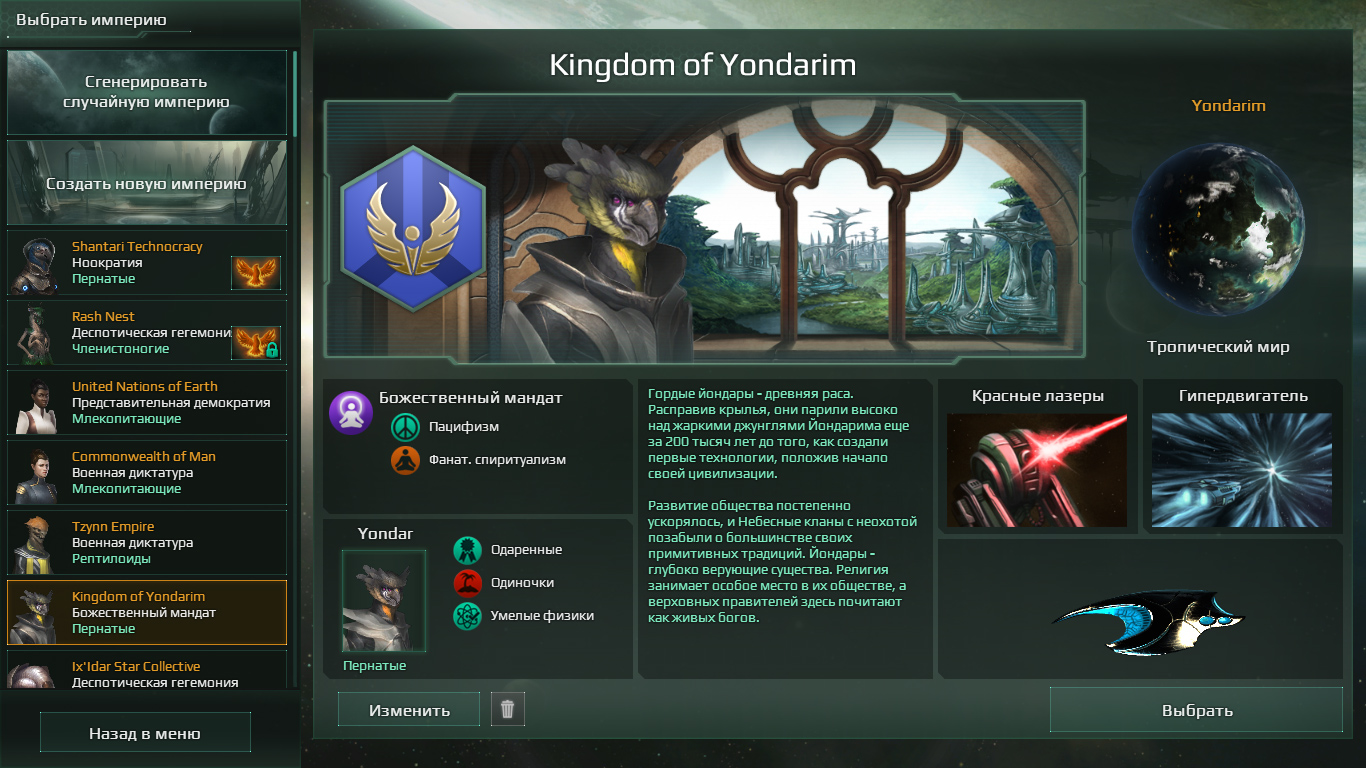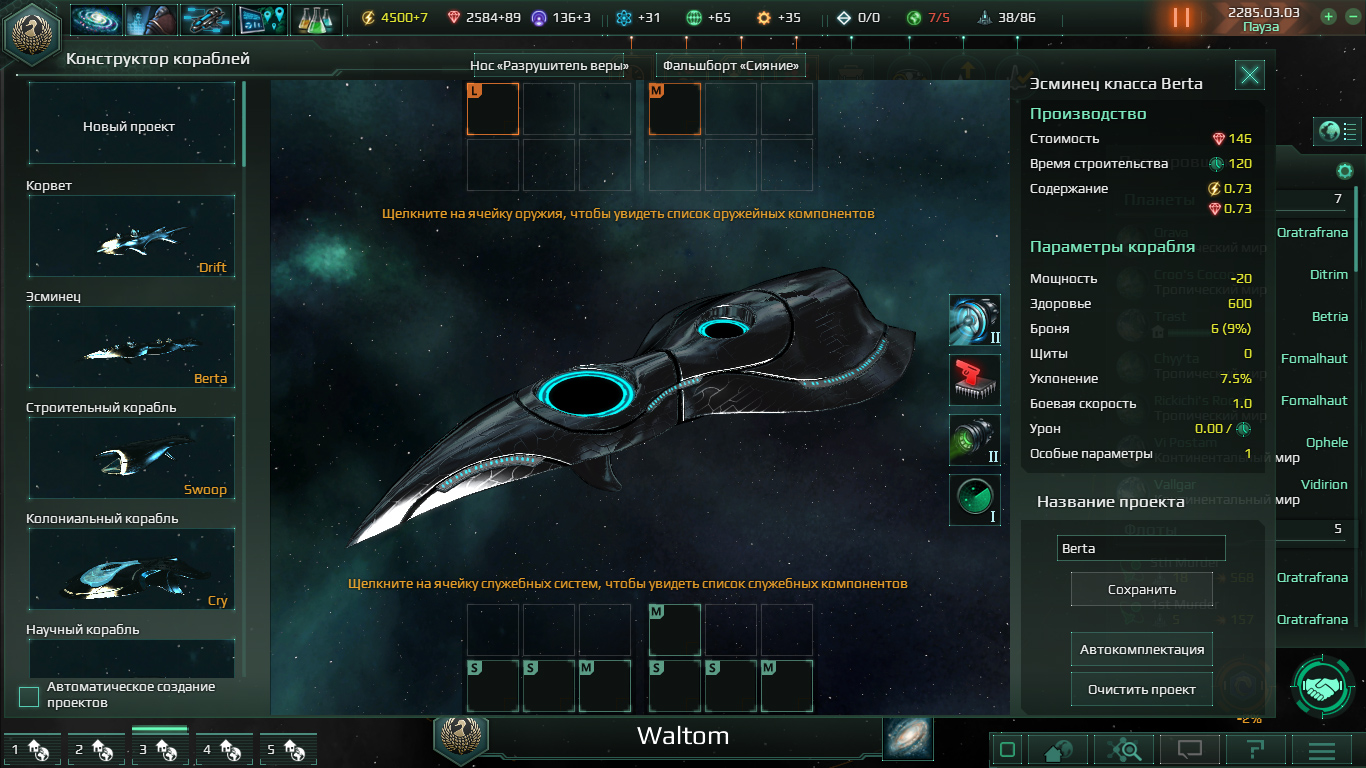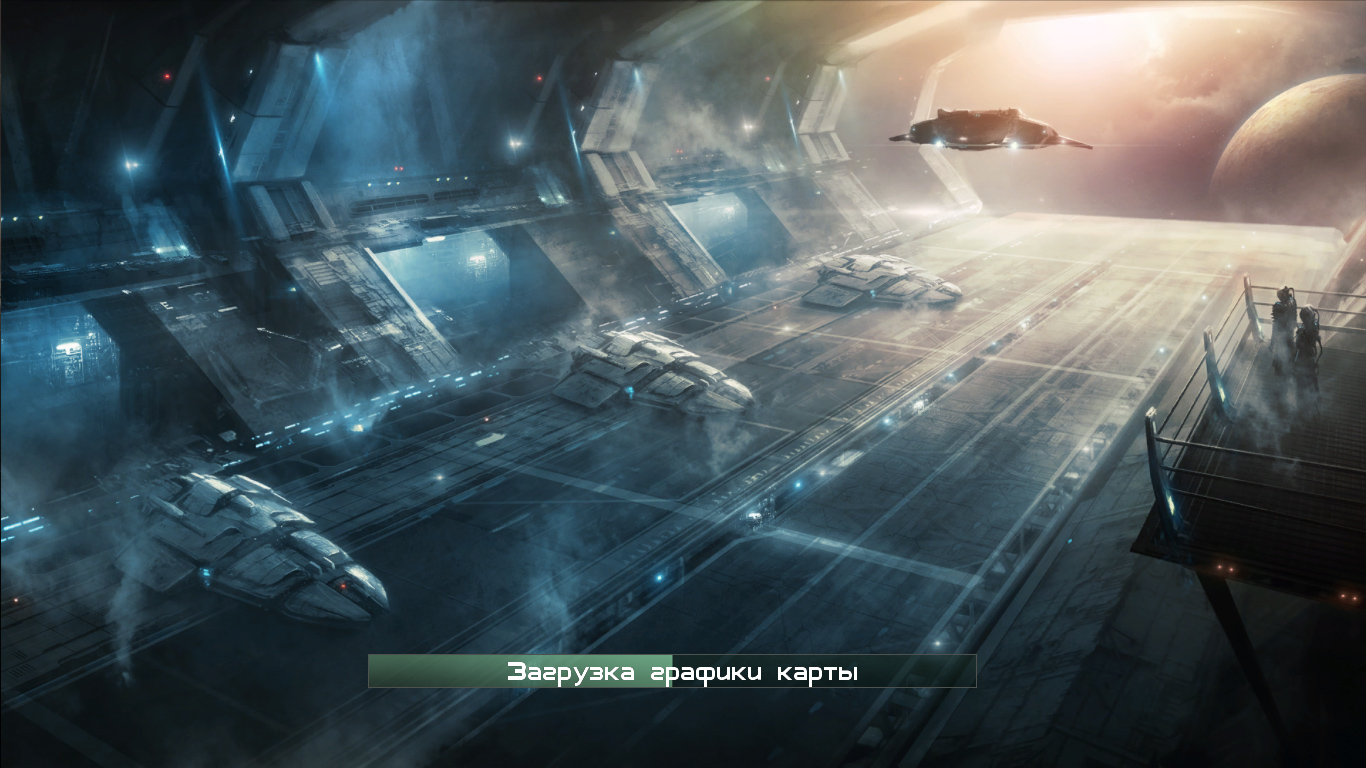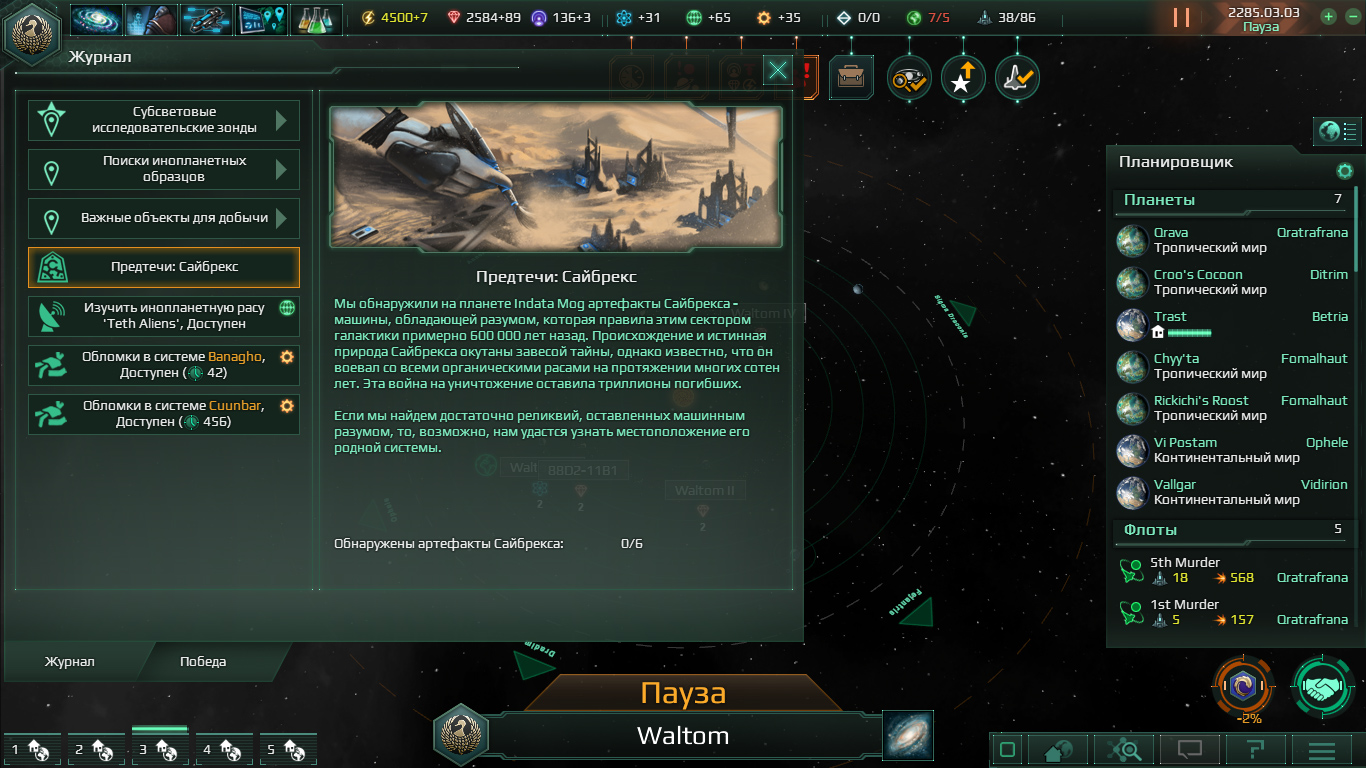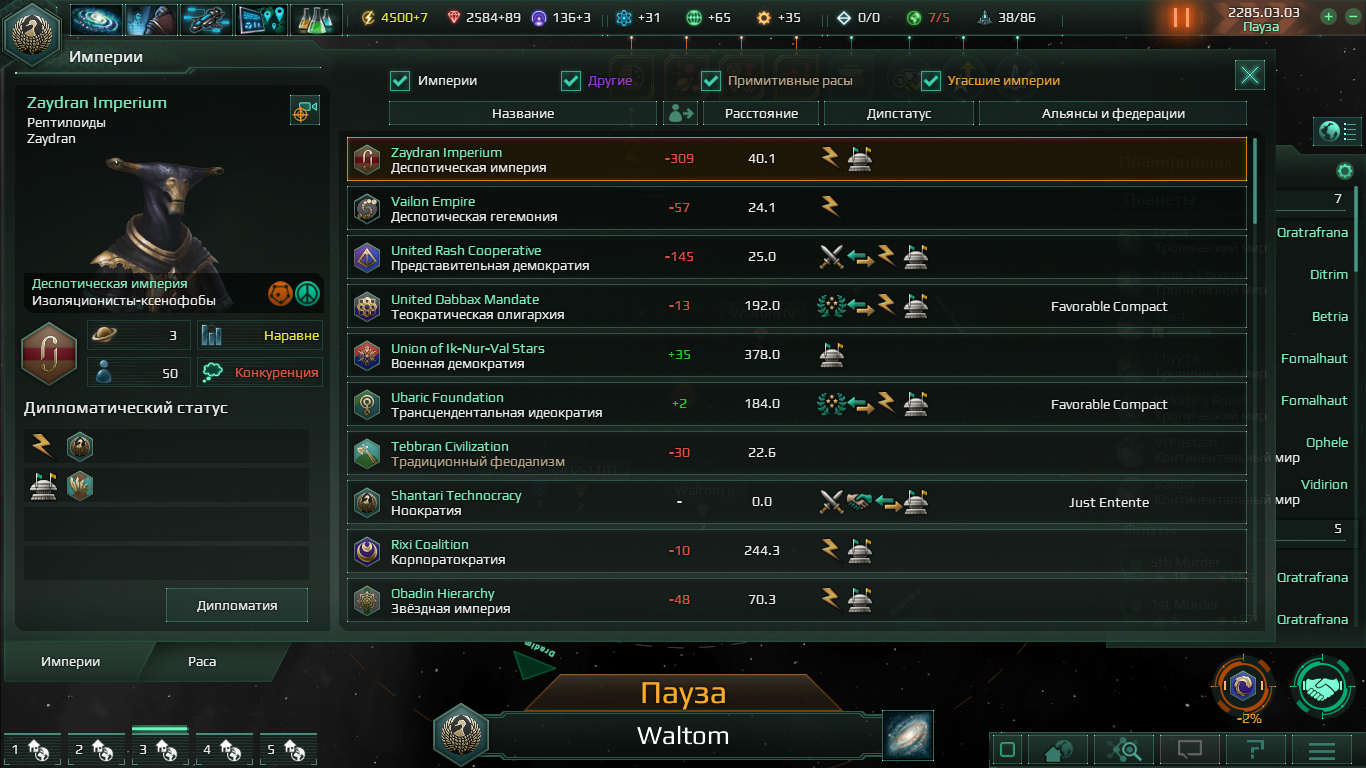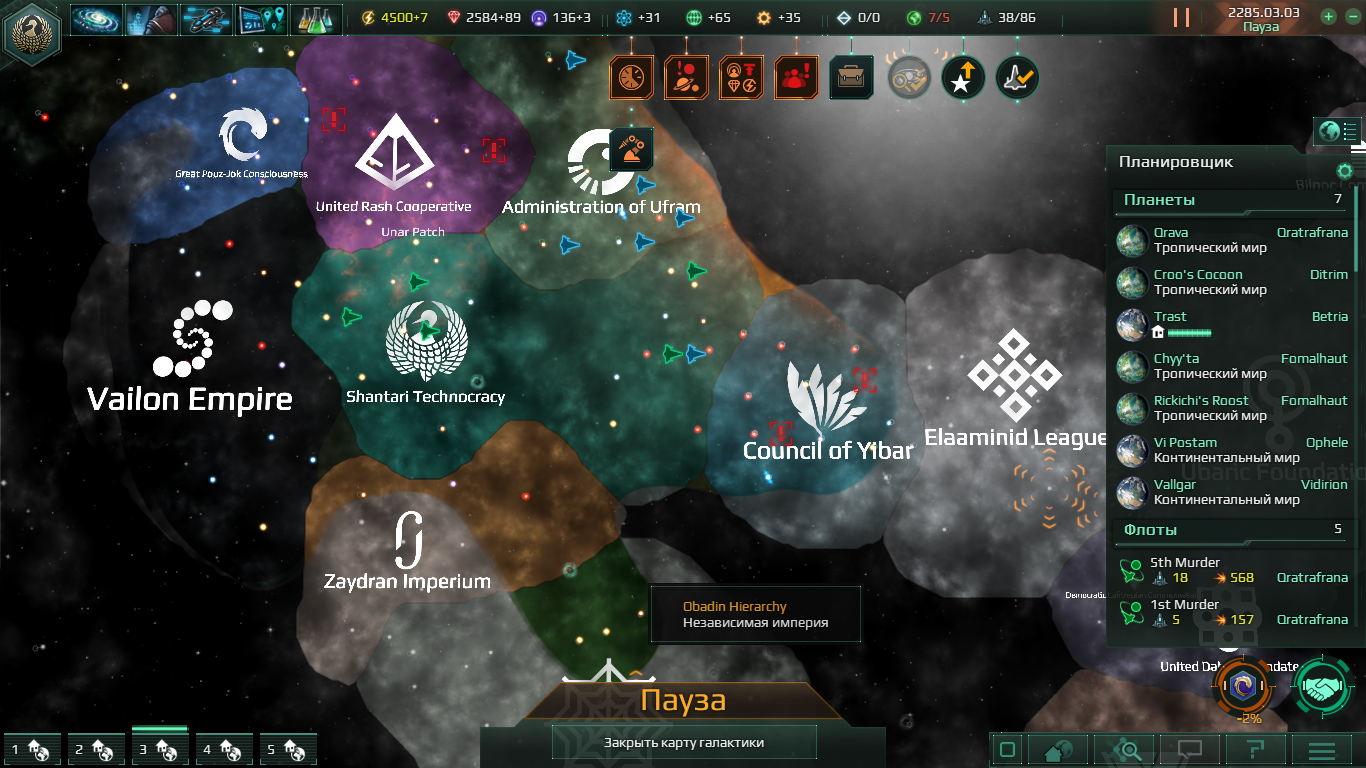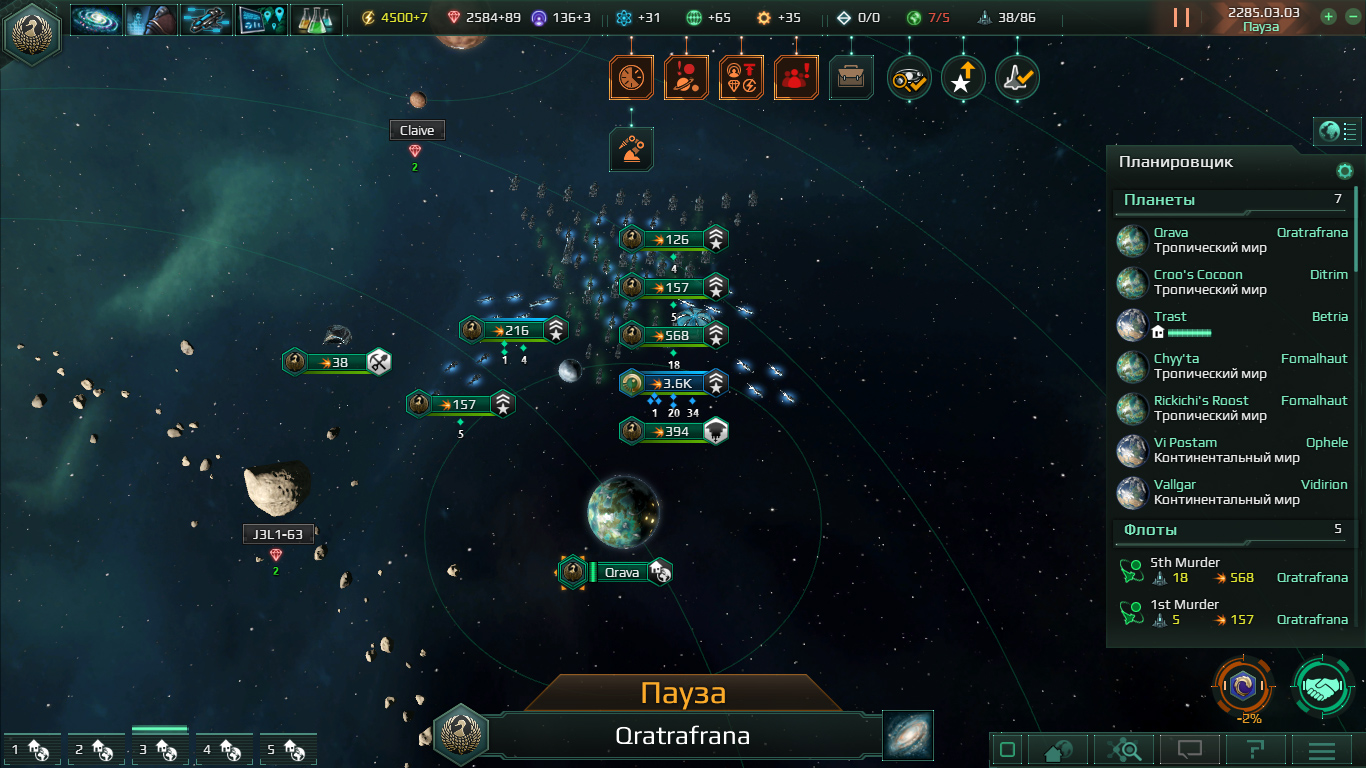
Более жирный и чёткий шрифт для русской локализации. Мод может устанавливаться отдельно от русской локализации ГЕКС, которая указана в требованиях, но изначально моды создавались совместно и для одновременного использования.